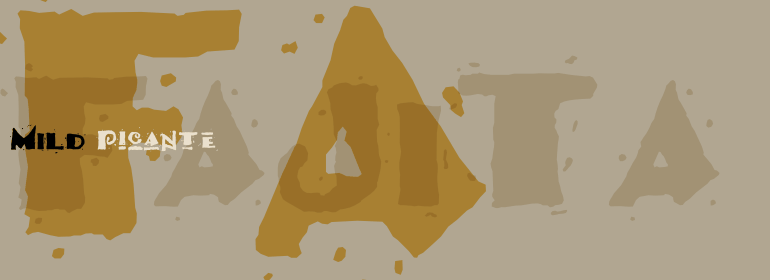
Fajita™
Fajita™,这款字体结构工整、笔画清晰,兼顾美观与易读性,适用于标题、正文、海报、包装、LOGO 等多种场景。字形优雅稳定,风格百搭耐看,适配日常排版与创意设计,让文字呈现更舒适、更具质感。Fajita™一笔一画,皆是细节,以均衡的比例、流畅的线条打造舒适视觉体验,字形端正大气,风格简约现代。无论是商业设计、品牌宣传还是日常排版,都能轻松驾驭,让文字更有格调与力量。Fajita™字体下载。
字体品牌: Image Club(Monotype) 设计师:Rubin,Noel 字体分类:衬线体 字体属性:外文 字符集:Unicode 发布时间: 2018